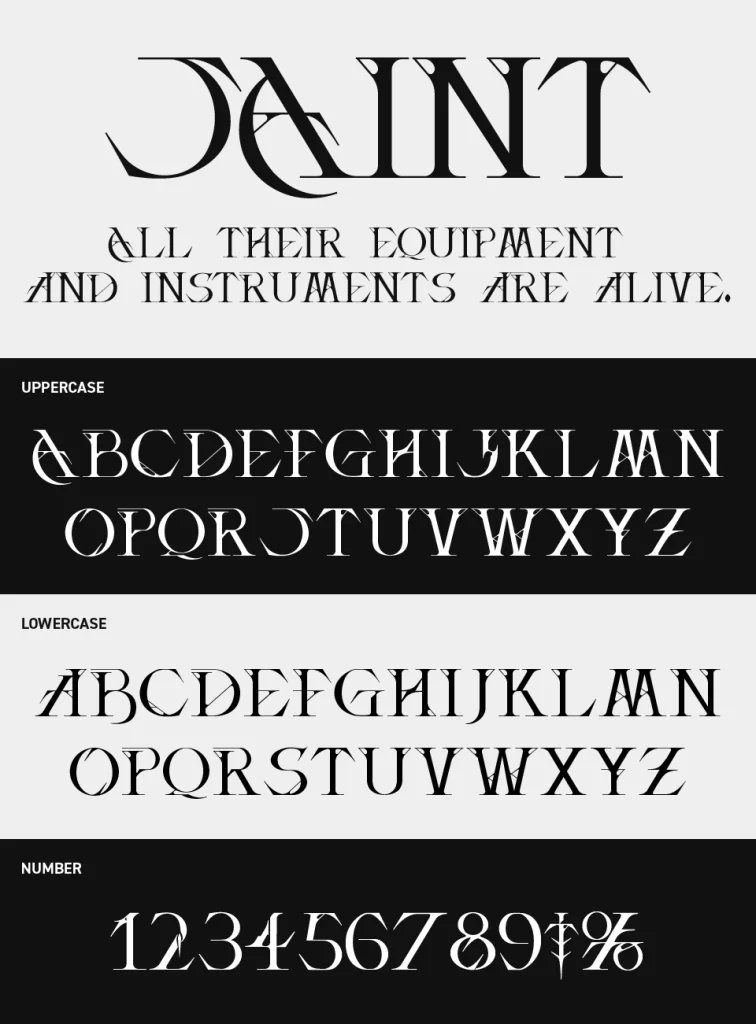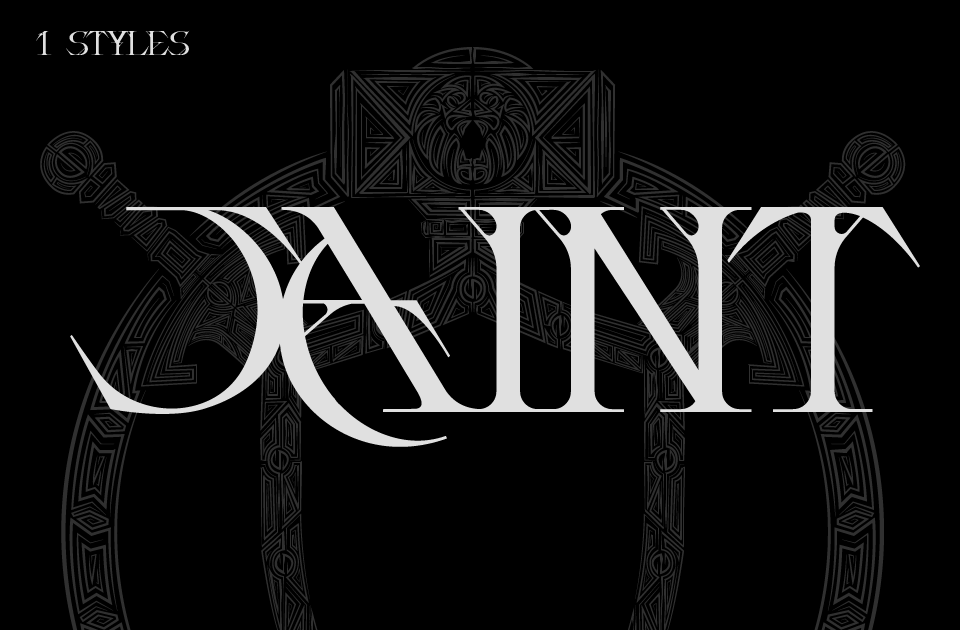
SAINT Font
Saintフォントは、クラシカルなセリフ体をベースに繊細な切り込みや装飾を加えた、気品と芸術性を兼ね備えたラグジュアリーなフォントです。
洗練された細いラインと大胆なコントラストが特徴で、高級感のあるビジュアルを美しく演出します。
一文字ごとに鋭いアクセントが加えられており、静かな中にもどこか緊張感を感じさせます。ファッションブランド、香水パッケージ、アートブック、ハイエンドなビジュアル制作など、上質で個性的な世界観を求める場面におすすめのフォントです。